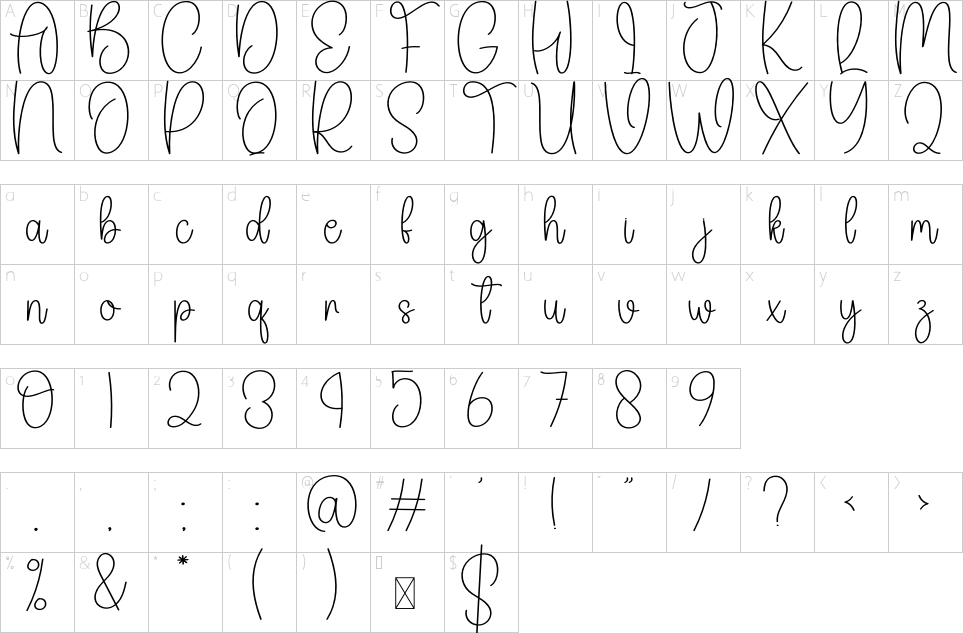
Autography Font – Download Grátis
Aqui está uma descrição em português para a página de download da fonte ‘Autography Font’, seguindo as instruções: Aqui está uma fonte gráfica de alta qualidade para seu projeto. Introduzida por scratchones, a Autography foi projetada com um design elegante e sofisticado que se destaca em qualquer projeto. Essa fonte não só é versátil e adequada para uso em materiais gráficos, mas também vem com uma facilidade de uso impecável. Descarregada 575 vezes, essa fonte de qualidade é um recurso valioso para designers, profissionais de marketing e até mesmo criativos de home office. Não espere mais para adicionar esta fonte à sua coleção e experimentar o poder da Autography.